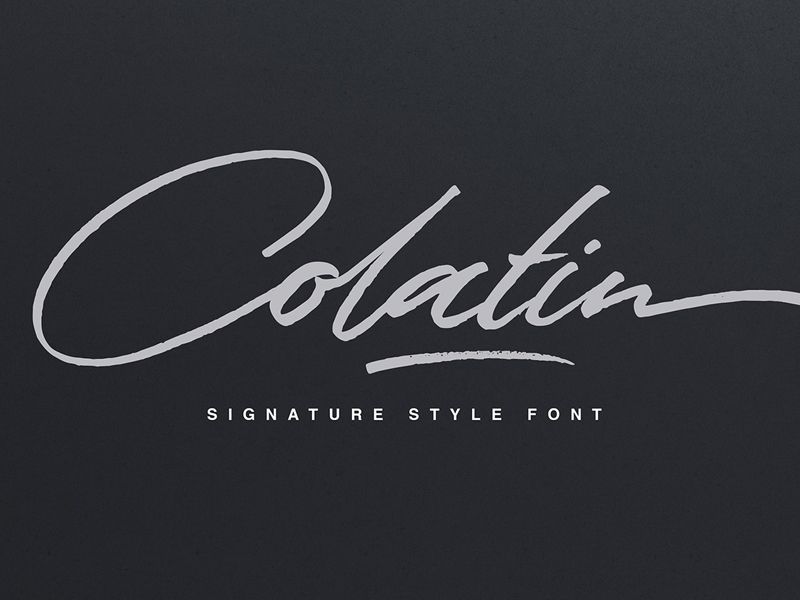
22 лучших шрифта для дизайна логотипов
Все, что вы выбираете для своего логотипа, является его неотъемлемой частью. Каждый элемент имеет одинаковую важность. Поэтому, когда дело доходит до выбора шрифтов, вам лучше не пренебрегать их значением.
Вы хотите, чтобы ваши шрифты дополняли дизайн логотипа. Это задача, в которой дизайнер должен продемонстрировать свою креативность и остроумие. При этом получить уникальные и адаптивные шрифты для логотипов становится все сложнее.
Если вы по ошибке выбрали неправильный или неподходящий стиль шрифта для своего логотипа, это может серьезно испортить весь дизайн. Чтобы помочь вам в процессе выбора шрифта, мы составили этот список. Надеемся, эти шрифты могут помочь дизайнерам создавать отличные логотипы с минимальными усилиями.
1. Frontage CondensedЭтот трехмерный шрифт передает удивительную атмосферу ретро. Первое впечатление от этого шрифта, — это старые классические фильмы и плакаты.
Это многослойная система шрифтов с жесткими и идеально выровненными буквами. В целом, это прекрасный шрифт для создания логотипа для различных ниш, таких как развлечения, классические и традиционные заведения или продукты.
Bodoni — один из любимых шрифтов дизайнеров на протяжении многих десятилетий. И поэтому он имеет классический оттенок, который вы можете увидеть во многих старых и известных брендах. Этот безупречный и тонкий стиль шрифта подходит для любой отрасли и любого логотипа. Есть плоские и незакрепленные засечки с двумя типами штрихов в шрифтах — жирным и тонким, что делает его очень элегантным и адаптивным.
3. Cassannet PlusCassannet plus — это уникальный шрифт без засечек, который выглядит одновременно профессионально и дружелюбно. Вы можете использовать этот простой и захватывающий стиль шрифта, чтобы сделать свой логотип броским и привлекательным. Как правило, он хорошо работает в качестве заголовка, но его можно использовать и в дизайне логотипов.
Southern scrip — это нежный рукописный шрифт. Поскольку он выглядит как красивый человеческий почерк, этот стиль может стать фантастическим логотипом любого бренда, который пытается передать эмоциональную, соединяющую, ценную и деликатную атмосферу. Он также олицетворяет достоинство и элегантность наряду с креативными и забавными характеристиками, которые делают любой логотип харизматичным и привлекательным.
Lora — это хорошо сбалансированный современный шрифт, широко известный своим основным текстом. Но этот стиль шрифта имеет очень важный и обоснованный вид, который можно адаптировать к любой отрасли и дизайну. Матовые кривые на контрасте с движущимися засечками делают этот стиль шрифта достойным и простым. Для потрясающей и необычной концепции этот стиль шрифта может выглядеть менее насыщенным.
Этот шрифт принадлежит к одной из известных категорий, называемых трафаретами. Частичные линии, круглые концы и острые засечки делают этот стиль эстетически красивым и захватывающим. Во многих логотипах известных брендов вы, должно быть, заметили использование жирных, простых и простых шрифтов, потому что этот тип шрифтов делает логотип вневременным, не зависящим от тенденций. Шрифт Zefani может придать роскошный вид и существенную привлекательность логотипу любого бренда.
7. BenchnineKiona — впечатляющий и надежный шрифт.
Он очень хорошо очерчен и подходит для многих красивых дизайнов. Утонченность и доминирование — ключевые черты этого шрифта. Таким образом, вы можете легко использовать его для создания сильного логотипа бренда, связанного со спортом или гламурными товарами. Этот шрифт позволяет с легкостью использовать его творчески для экспериментального дизайна из-за его высокой адаптивности.
Вы можете увидеть уникальных и креативных персонажей в стиле шрифта Nixmat. Минималистичные и жирные штрихи с невероятными линейными деталями делают этот шрифт более привлекательным и захватывающим. Он идеально подходит для логотипов и фирменного стиля. Вы можете придать своему логотипу элегантный, сильный, уверенный, креативный, привлекательный и современный вид с помощью этого стиля шрифта. На Envato можно приобрести этот стиль шрифта для личного или профессионального использования.
Intro — один из лучших классических тематических шрифтов, в котором есть небольшой намек на засечки и гротеск.
Вы можете заметить в этом стиле креативные изгибы и прямые концы, которые делают его одновременно привлекательным и традиционным. Бренд может отражать веру, привязанность и доминирование в своем логотипе с помощью этого шрифта.
Этот красивый шрифт в нижнем регистре доступен для бесплатной загрузки на веб-сайте Behance. Вы можете взять его для личного и профессионального использования. Сильно изогнутая тема без каких-либо строгих краев делает этот стиль шрифта интересным для творческого, молодого и легкого дизайна логотипа. Вы можете выбрать его для одежды, продуктов питания и напитков или бренда, связанного с образом жизни.
La Macchina — идеальный шрифт, чтобы подчеркнуть роскошь и уверенность в дизайне. Этот шрифт имеет корни в каллиграфии, поэтому кажется более индивидуализированным и традиционным. Если вы хотите, чтобы ваш логотип был футуристическим и вневременным, вы должны выбрать такие шрифты, как La Macchina.